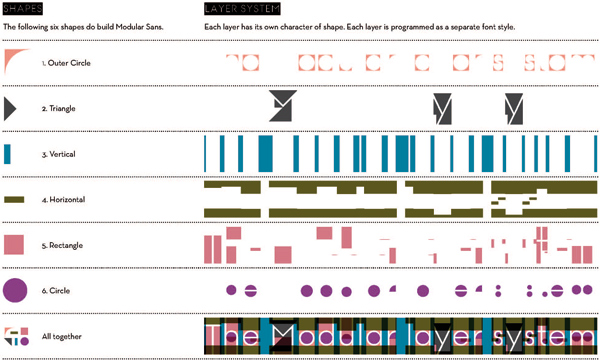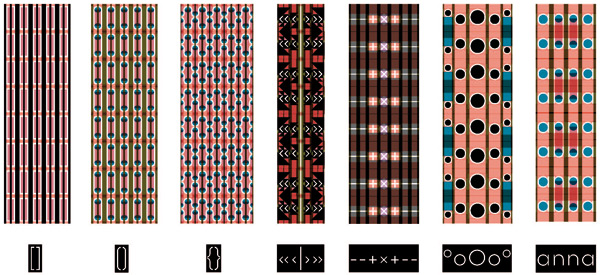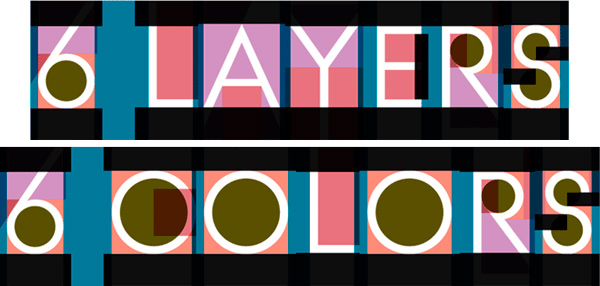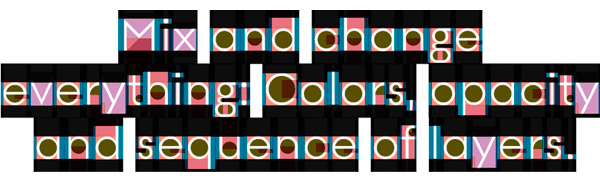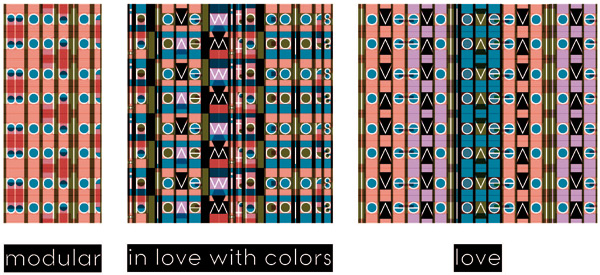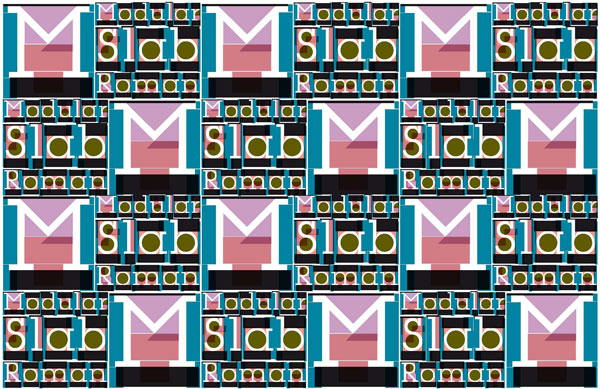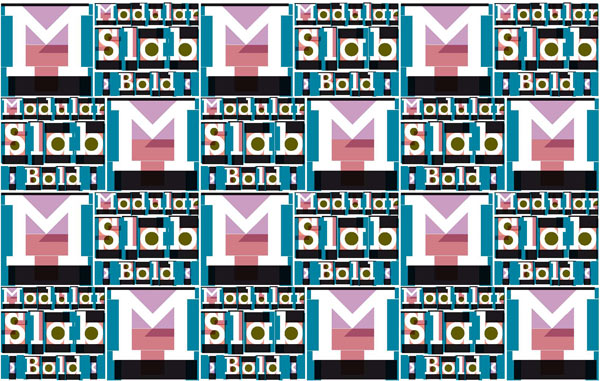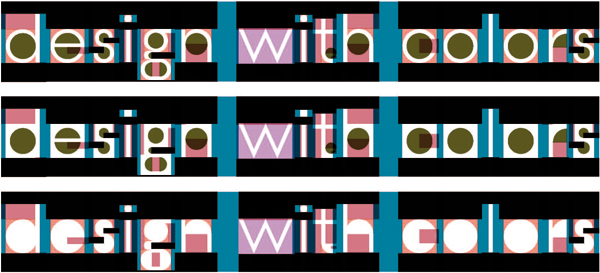
Modular, el último proyecto tipográfico de Letterwerk, permite generar tipografías a partir de la superposición de seis capas de color que utilizan patrones gráficos predeterminados. Estos patrones permiten la visualización de los caracteres según las diversas modificaciones cromáticas del espacio negativo que existe entre las letras.
Presentación de Modular en After Effects, Letterwerk, 2012.
Modular de Letterwerk, 2012.
Modular, Letterwerk, 2012.
Modular, Letterwerk 2012.
Modular Sans Roman, Modular Slab Roman y Modular Slab Bold son las tres versiones que Letterwerk ofrece a través de su web y que pueden adquirirse online. Gracias a la gran armonía de sus proporciones en la combinación de elementos rectos y curvos y a sus remates de palo seco y en mecano se adaptan con facilidad a la construcción y al control digital de los patrones geométricos que permiten su visualización.
Modular Sans Roman, Modular Slab Bold, Letterwerk, 2012.
Modular Slab Roman, Letterwerk, 2012.
Modular Slab Bold, Letterwer, 2012.
El estudio Letterwerk, fundado en el año 2008 por Fabian Widmer y Dominique Boessner, cuenta con dos sedes en las ciudades de Berlín y Zürich y, además de estar especializado en diseños de tipografías, desarrolla habitualmente proyectos de gráfica editorial, identidad corporativa, señalización y exposiciones.
Modular Sans Roman, Letterwerk, 2012.
Patrones de Modular Sans Roman, Letterwerk, 2012.
Modular, Letterwerk, 2012.